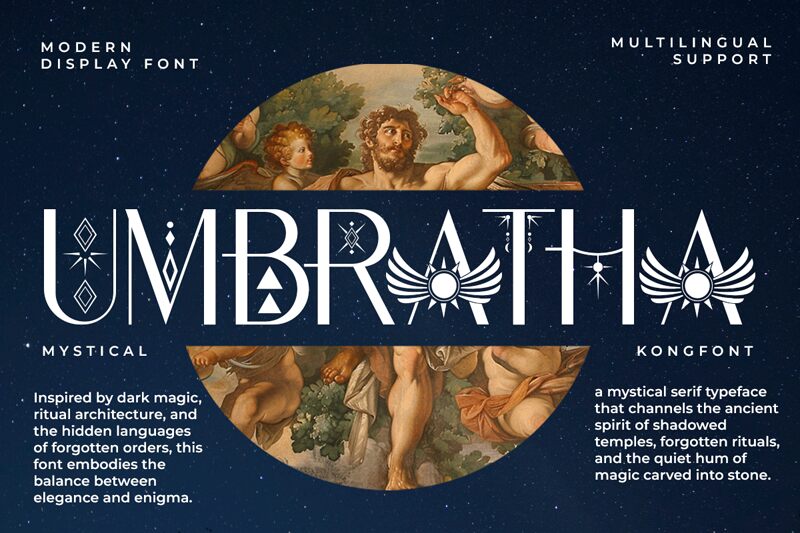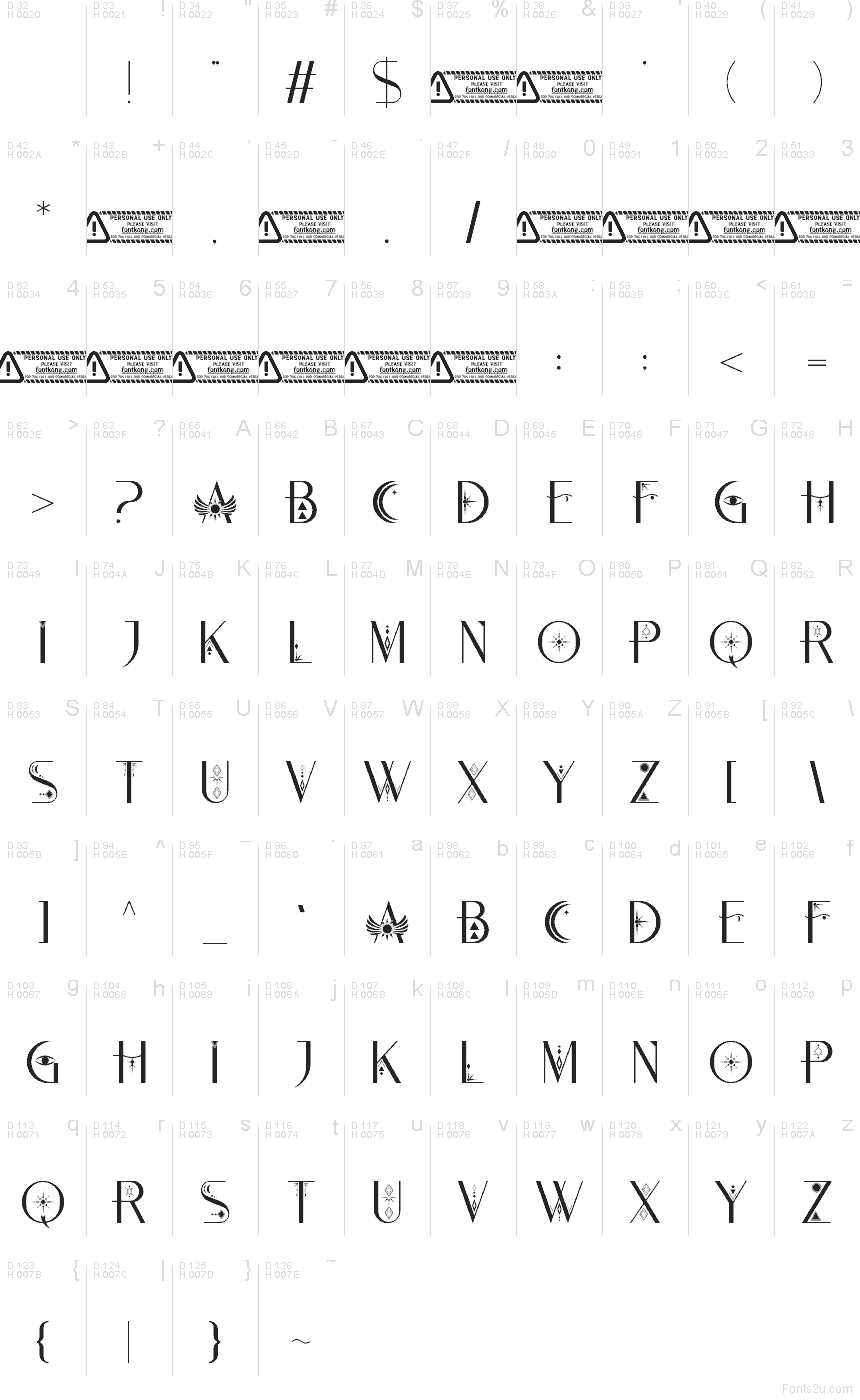
Umbratha de Kong Font est une police d'affichage gratuite à l'allure occulte, dotée d'une silhouette Art Déco et d'une ambiance rituelle, presque emblématique. Les lettres mêlent des formes classiques élancées à des triangles acérés, des inserts en losange, des barres transversales et un motif de soleil ailé, conférant à la police un aspect autant construit à partir de symboles que de traits.
Elle est idéale pour les titres d'affiches, les pochettes d'albums, l'image de marque dans l'univers fantastique, les emballages de tarot et les flyers d'événements où le lettrage doit agir comme un insigne. En tant que police gratuite, Umbratha convient également aux textes de couverture courts, aux monogrammes et aux cartons-titres, surtout lorsque vous souhaitez que les majuscules portent une note mystique et cérémonielle par elles-mêmes.